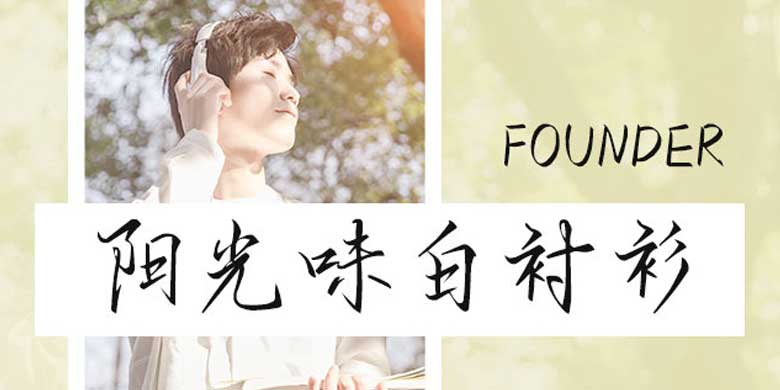
方正手跡-陽光味白襯衫是一款極具傳統(tǒng)書法味的字體,很好的取法了書法中筆畫的一些形態(tài),以及一些行筆方式。構(gòu)字上也不拘泥于傳統(tǒng)構(gòu)字方式,更多的靈活多變。適用于文藝類的書刊、品牌廣告和產(chǎn)品包裝設(shè)計,以及社交網(wǎng)絡(luò)的個性化用字。歡迎喜歡方正手跡-陽光味白襯衫字體的朋友前來下載使用。